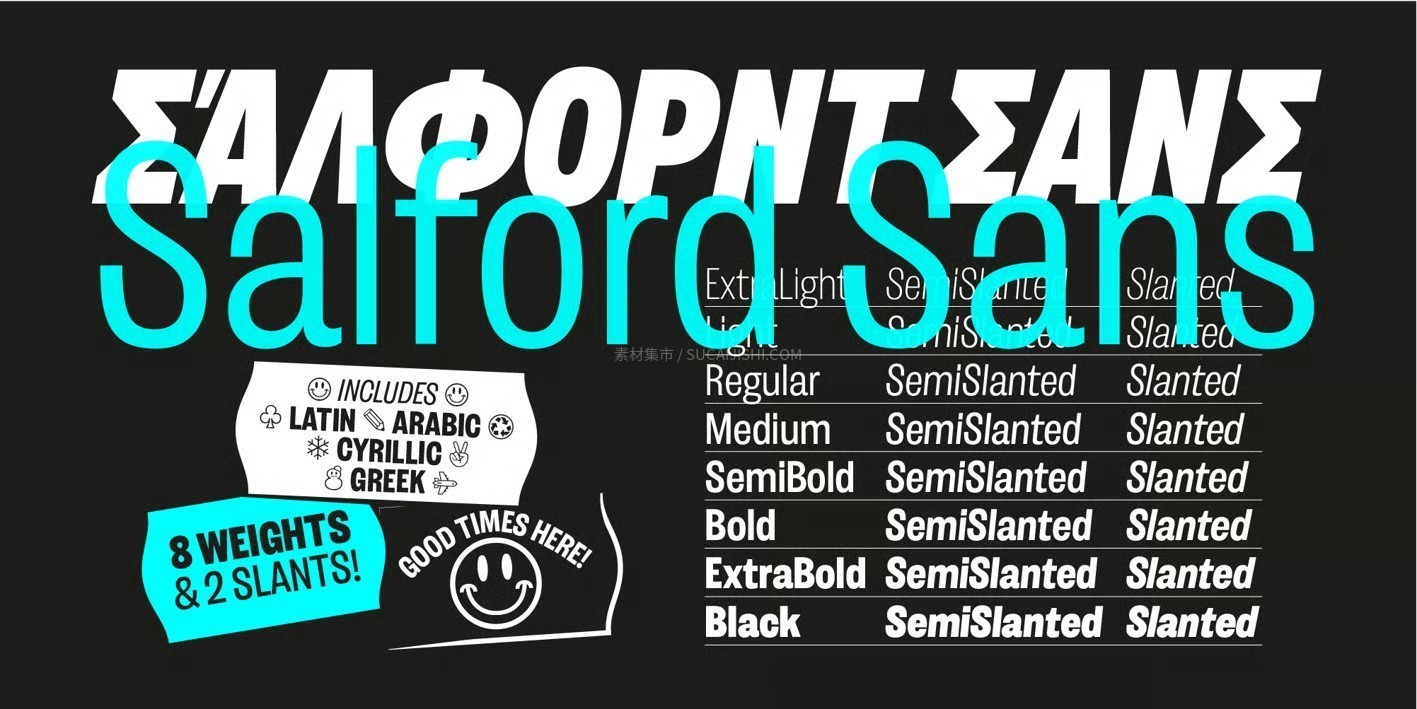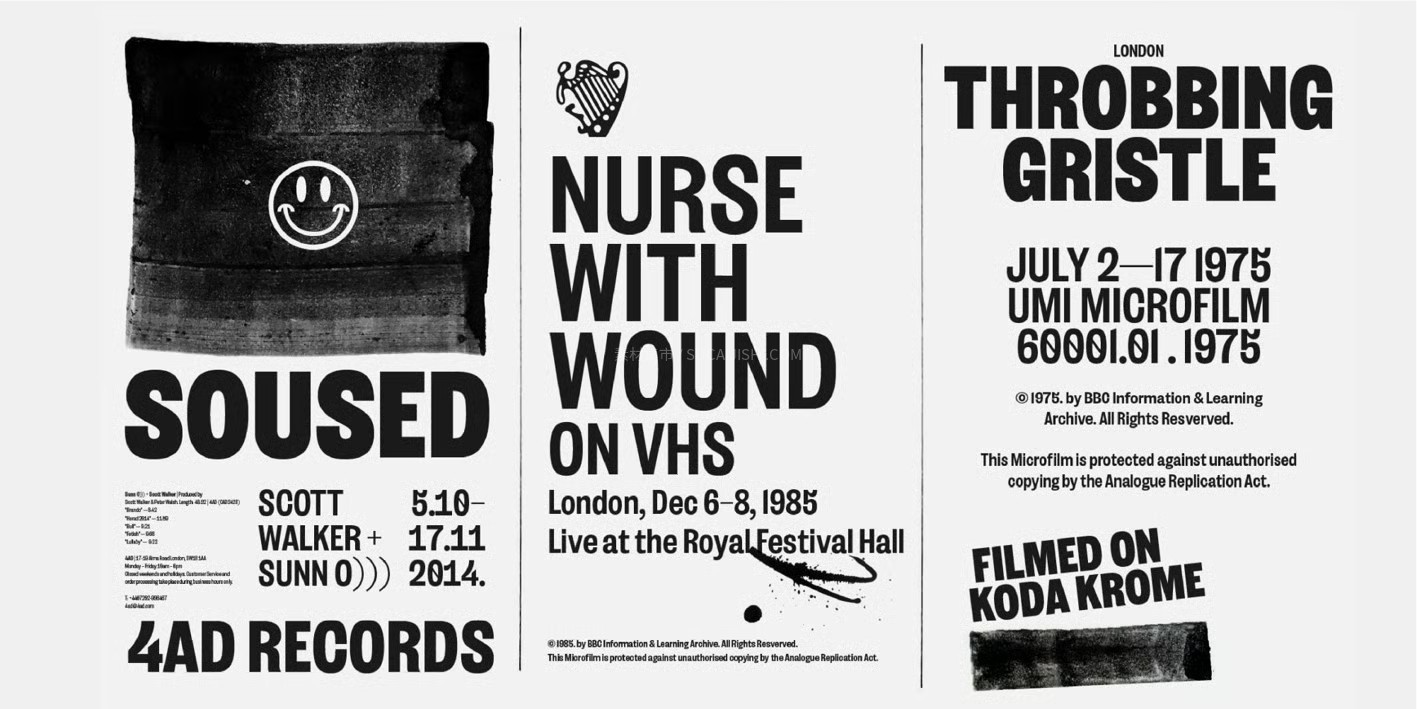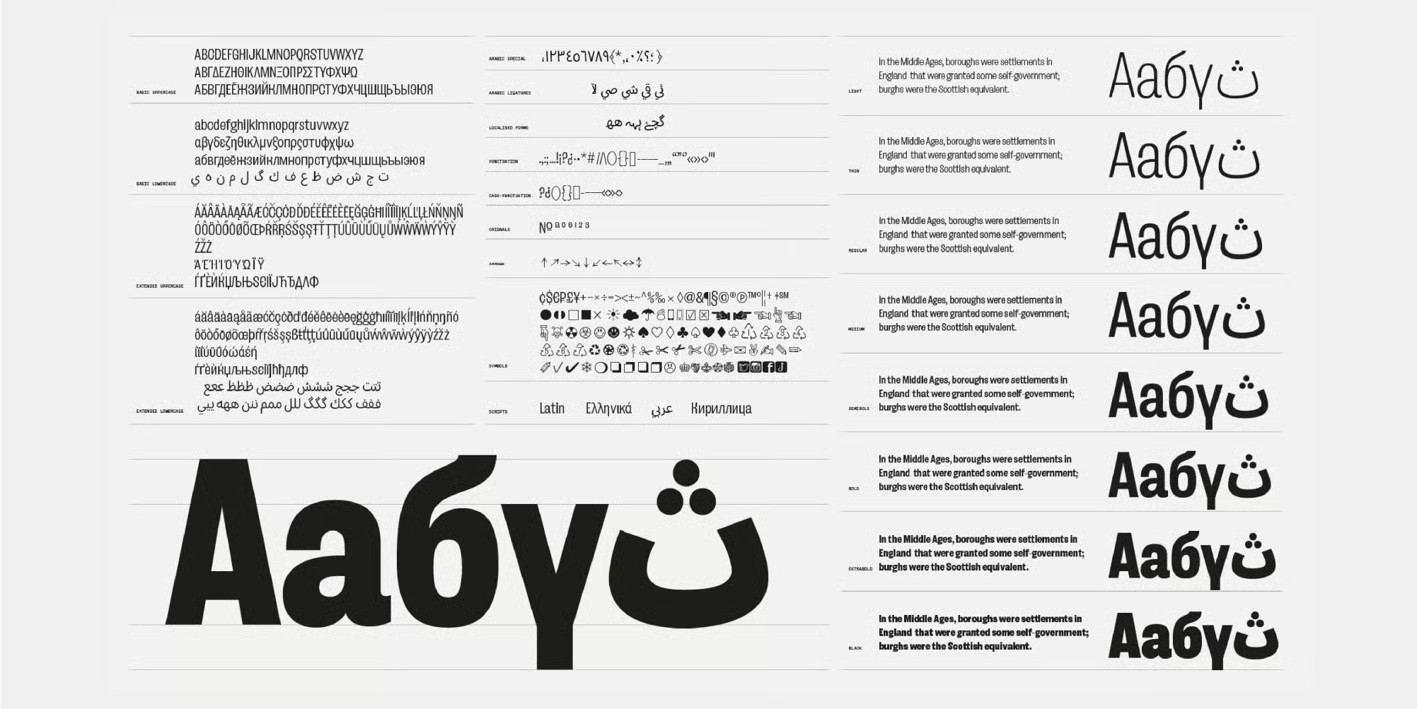
Salford Sans 多语言窄体无衬线字体完整版
Salford Sans 是一款对传统英式窄体(British Condensed)无衬线字体理念的现代演绎。它不仅拥有稳健、实用的工业骨架,更在笔画细节中注入了微妙的时尚手工质感。Salford Sans 专为追求严肃性、国际化且易于沟通的视觉传达而设计,是高端标题、社论排版及展示性作品的理想选择。在全球范围内,它已成为兼顾时尚审美与功能主义的设计师首选。
支持 OpenType 语言功能、可变倾斜轴 (Variable Slant) 调整
多语种排版: 完美涵盖扩展拉丁文、单调希腊文、阿拉伯文及西里尔文。
全套字重: 包含 8 种字重,涵盖匹配的倾斜 (Italic) 与半倾斜 (Semi-Slant) 样式。
本地化支持: 包含一系列本地语言功能,确保多文化背景下的排版专业性。
丰富符号: 内置完整的符号库与简洁的字体特征,适配各种复杂的版式需求。